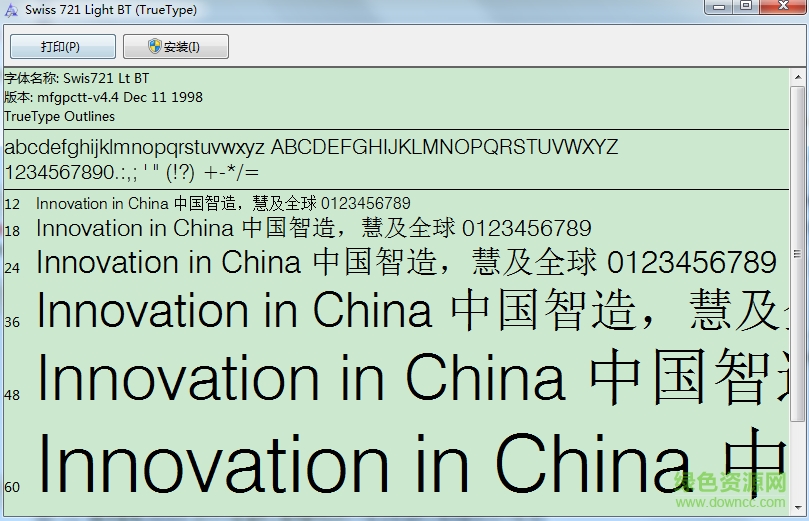
swis721 lt bt字體是一款非常實用的普通西方字體,這款英文字體十分優(yōu)美,字形筆畫纖細,非常好看,用戶英文創(chuàng)意設計再合適不過了,更多類似字體盡在綠色資源網(wǎng)!喜歡的朋友歡迎來綠色資源網(wǎng)免費下載使用。
swis721 lt bt字體字形清秀大方,華而不浮,非常適合廣告設計、平面設計、印刷包裝、正文標題等人員使用。